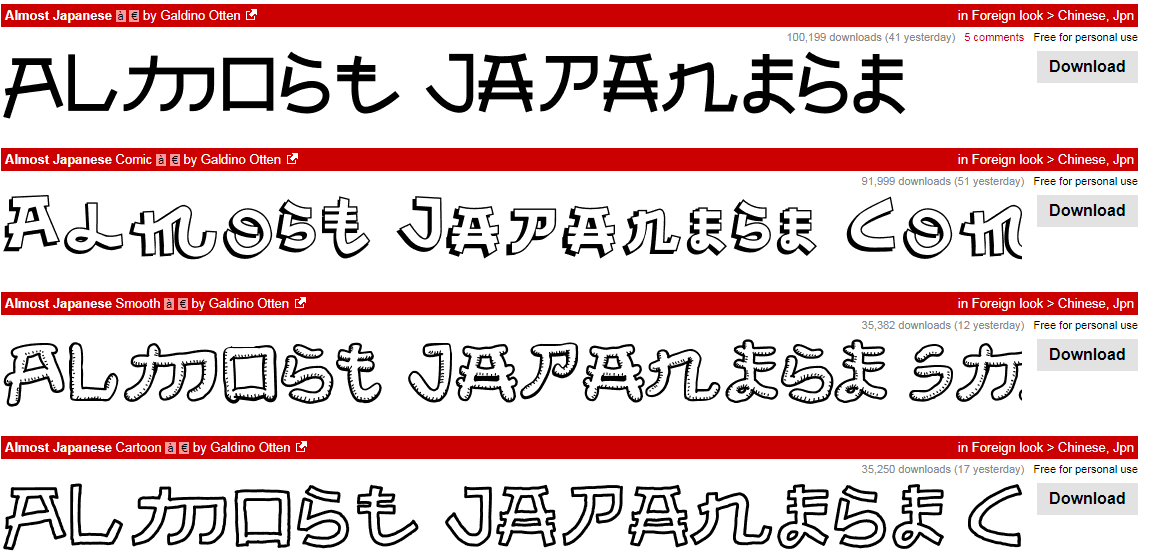
font nhật
Ý mà nói là font nhật cũng không được , nó là các font có dạng na ná các chữ nhật thôi . Dạng vậy chứ tui cũng chẳng biết miêu tả sao . Không dài dòng thì tui sẽ thả preview kèm tên font để mọi người lên dafont.com tìm nhé <3
1. Almost Japanese
Ở đây thì tui khuyên dùng bản regular thôi =)) .
2. Brushido
3. Far East
4. Fujimaru
5. Hirosh
6. Japanese Style
7. Kashima Brush
8. Manga
Manga thì có manga này manga nọ phải không cả nhà
10. Sunrize
11. Makise
12. Japanola
13. Wacky Sushi
Fact : Ghi cho vui chứ tui cũng chả biết font nhật với trung khác nhau ở đâu đâu =))